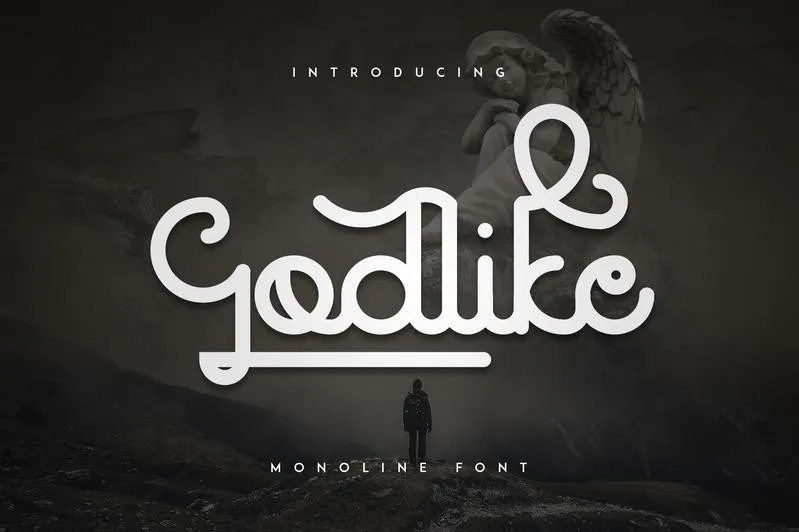
Godlike Font + Logo Templates – Download Grátis
Godlike Font + Logo Templates é uma elegante fonte display monoline com ângulos redondos que oferece uma versatilidade incrível, funcionando maravilhosamente tanto em grandes como em pequenos tamanhos. Esta fonte está perfeitamente projetada para uso em projecções de marca, designs de móveis de casa e embalagens de produtos – ou simplesmente como uma superposição de texto estilizada sobre qualquer imagem de fundo. O designer vp_creative_shop criou este design único que se destaca no seu campo, oferecendo inúmeras possibilidades para personalização e customização. Ideal tanto para designers profissionais quanto para iniciantes, o Godlike Font + Logo Templates é uma fonte imprescindível para quem busca estilo e versatilidade em cada projeto de design gráfico.